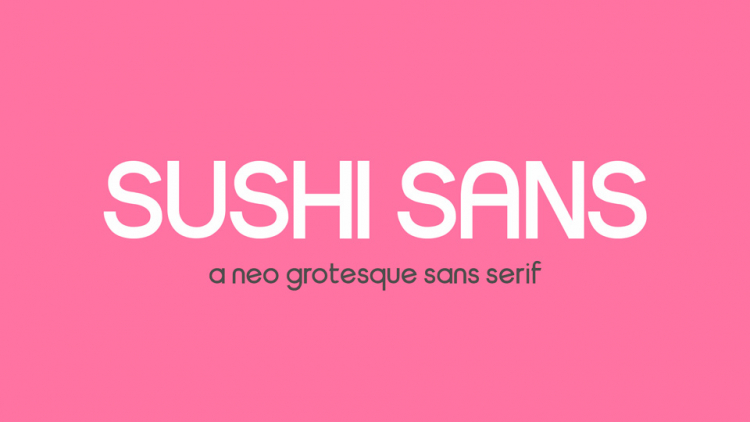
Sushi Sans Font
Sushi Sans é uma fonte do tipo sans-serif que traz uma experiência visual moderna e minimalista para seus projetos digitais. Inspirada na simplicidade do sushi, sua linhas retas e elegantes criam um desenho atraente e arredondado ao mesmo tempo. Este neo-grotesque font é perfeito para aplicações que exigem uma aparência clara e sofisticada, seja em posters de alto impacto ou em headlines curtas e agradáveis aos olhos. Com Sushi Sans Font, você ganha uma ferramenta versátil para estilizar seu conteúdo, desde textos grandes até detalhes menores. Suas linhas leves garantem um texto fácil de ler e profundo, ajudando a transmitir seu mensagei claramente em qualquer circunstância visual. Perfecto para criar uma identidade gráfica forte e harmoniosa. Para tornar seus projetos ainda mais impactantes, Sushi Sans é especialmente ideal quando combinado com outras fontes do tipo serif ou de estilo antiqua.